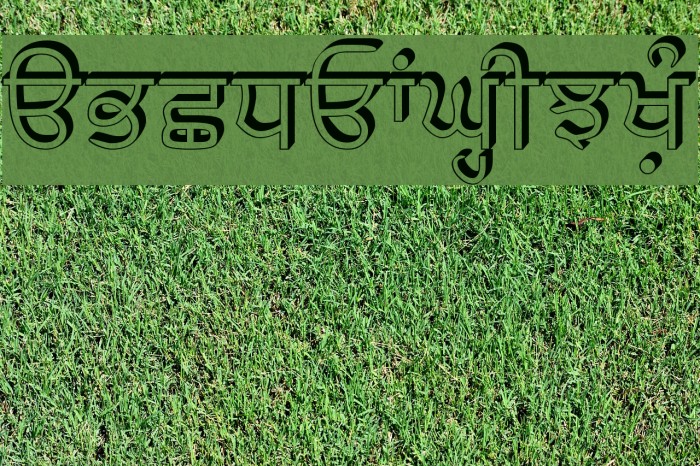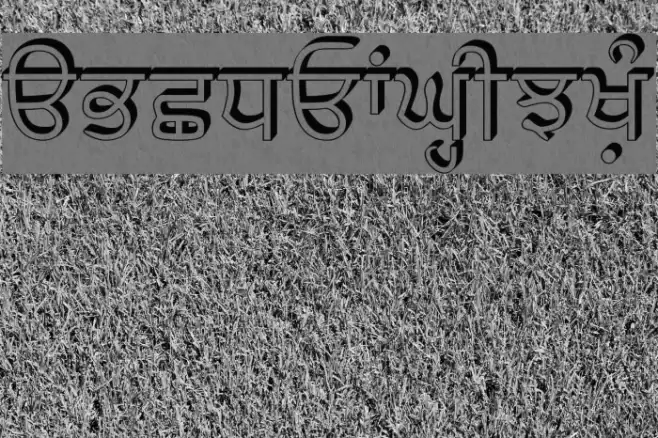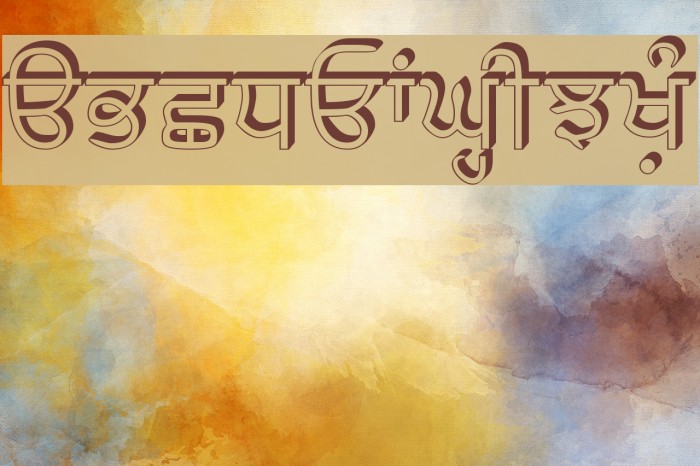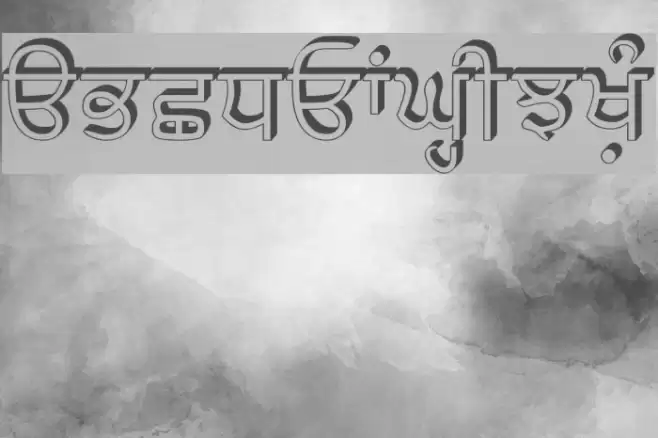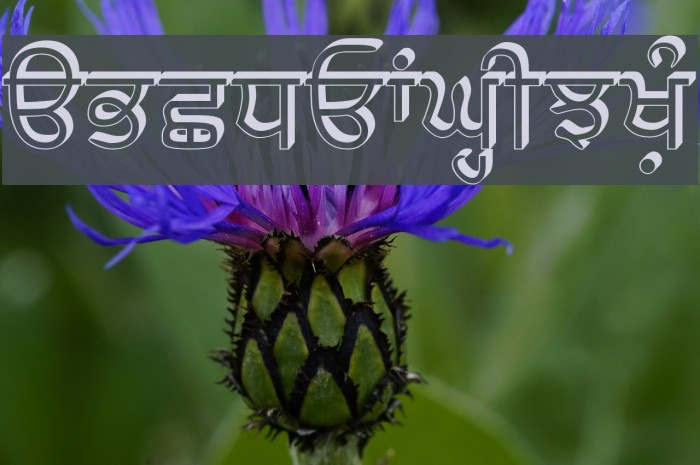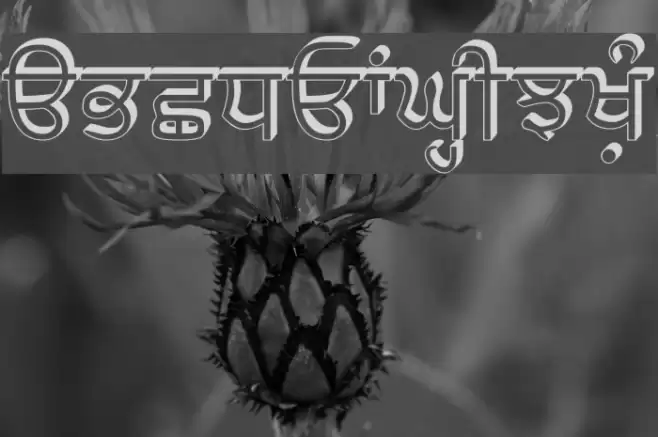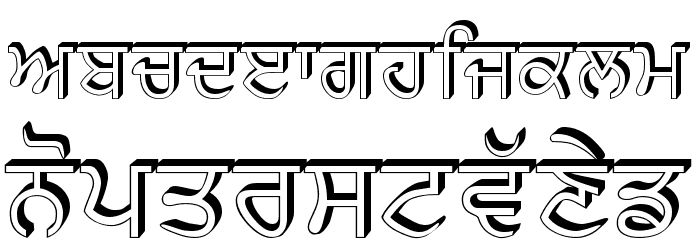
SamtolRaised Font
| おすすめプロジェクト | This font is perfect for projects that require a strong visual impact, such as posters, banners, logos, and branding materials. Its unique style can also be used in digital media, advertisements, and packaging design. |